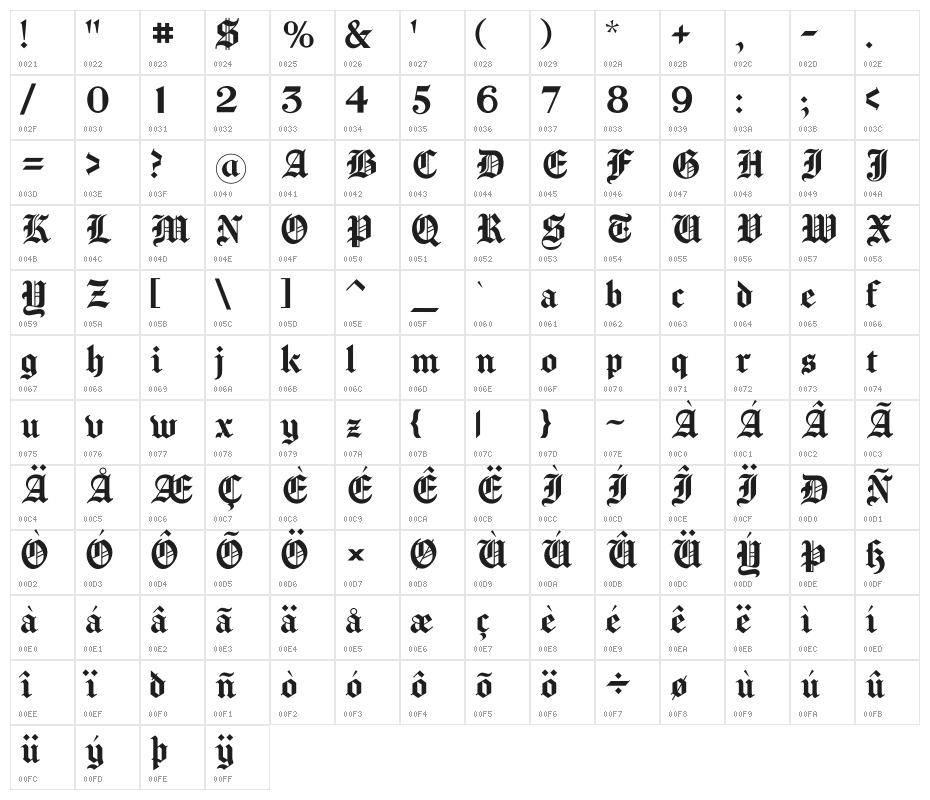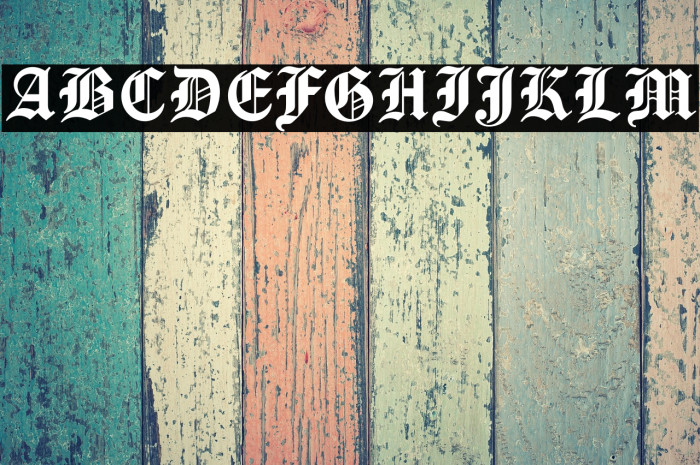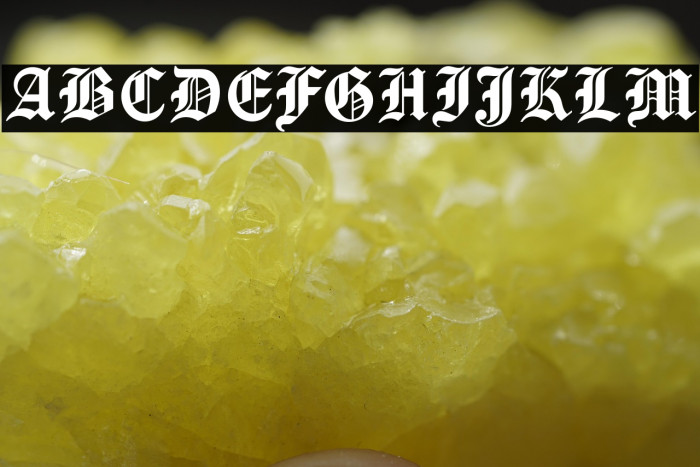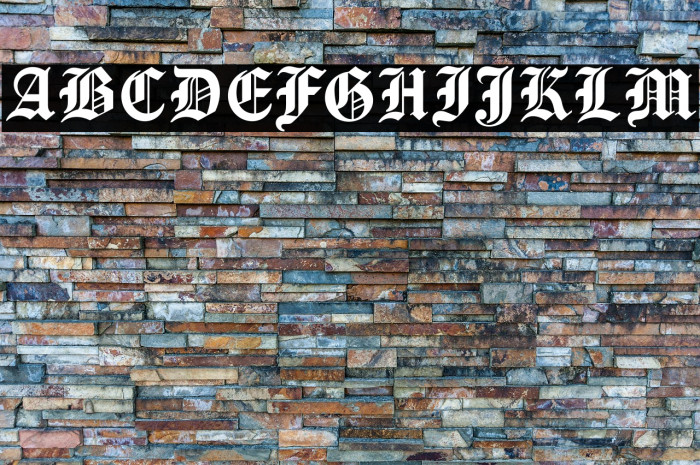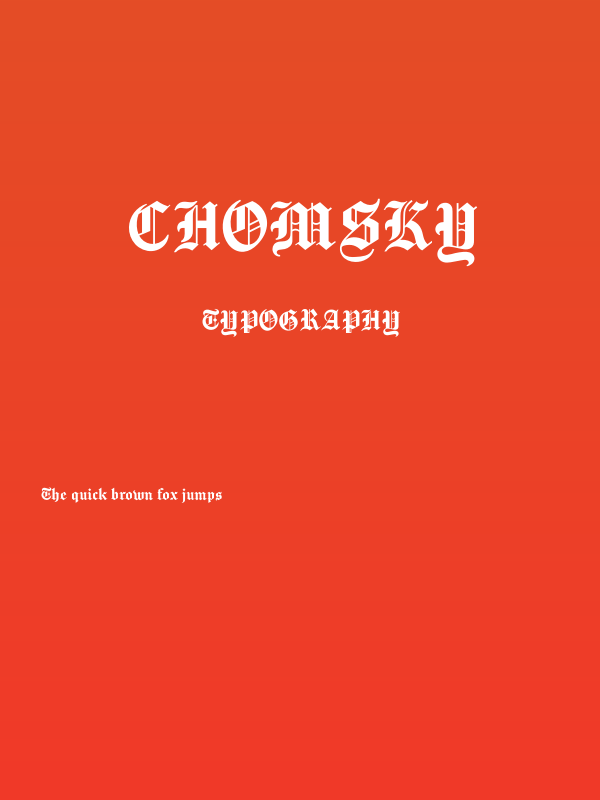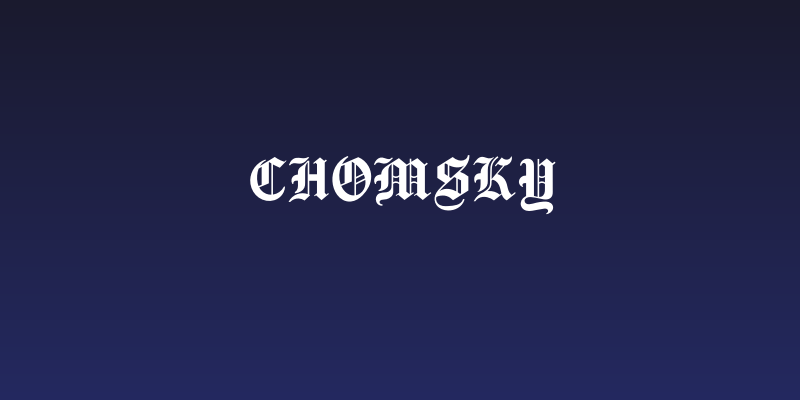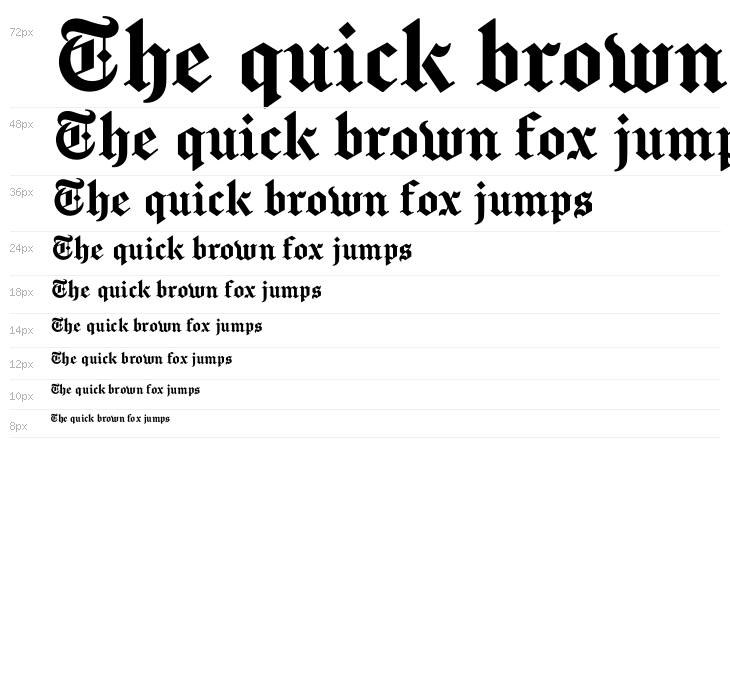
Chomsky Font
| Gesamtstil | Vintage |
| Anwendungsfall | Headlines, Logos, Decorative |
| Vorgeschlagene Projekte | Ideal for projects that require a historical or gothic touch, such as book covers, posters, or branding for vintage-themed products. |